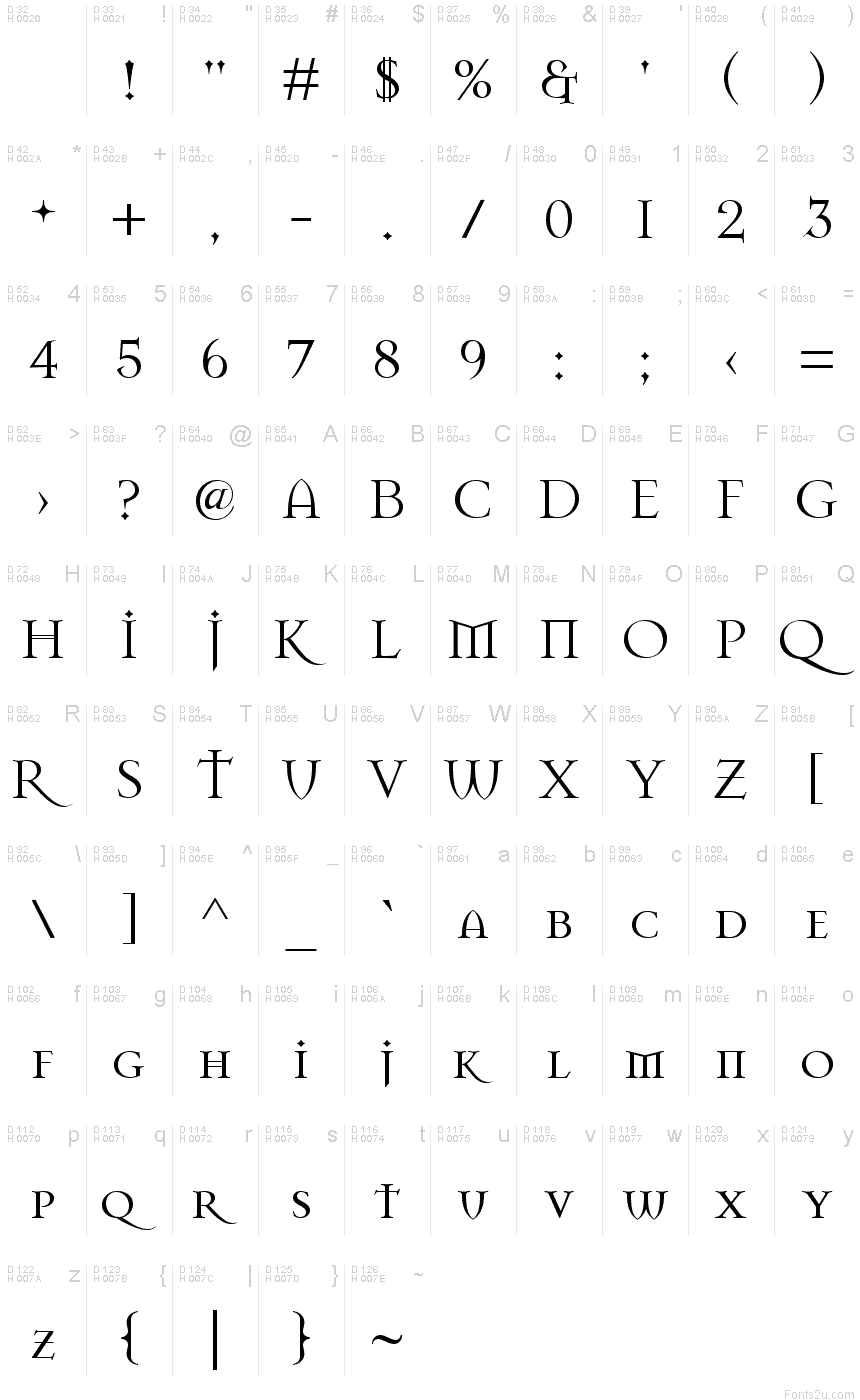
NK20 di Nikola Kovanovic è un carattere serif cirillico gratuito dal fascino raffinato e d'altri tempi. Le lettere appaiono formali ed equilibrate, costruite su verticali decise, tratti di connessione sottilissimi e alcune curve calligrafiche affilate che conferiscono al carattere un finish leggermente teatrale.
È ideale per copertine di libri, poster culturali, titoli di riviste, grafiche museali e brevi intestazioni editoriali dove quel contrasto può fare la differenza. Essendo un font gratuito, si adatta bene anche a monogrammi e cartelli, soprattutto se cerchi una voce classica con un tocco di eleganza, invece della solita asciutta rievocazione storica.